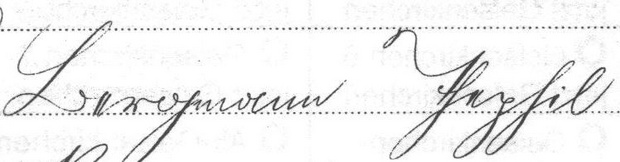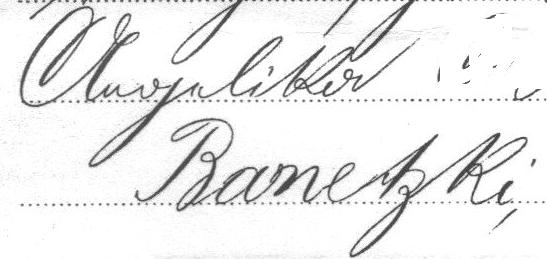
Was heißt das?
Ich hoffe, dass mir hier jemand helfen kann. Das Foto 1 zeigt einen Ausschnitt aus einer Geburtsurkunde von 1930. Es müsste sich um eine Berufsbezeichnung handeln. Leider habe ich keine Ahnung, was das bedeuten soll.
Das zweite Foto ist ebenfalls eine Geburtsurkunde, diesmal von 1903. Hier handelt es sich wahrscheinlich um eine Berufsbezeichnung, gefolgt von einem männlichen Vornamen.
Foto 3 müsste ein weiblicher Vorname sein, gefolgt von einem Nachnamen.
Ich habe das Gefühl, der Standesbeamte hat frei Schnauze irgendwas geschrieben, reines Sütterlin ist das nicht.
Beim dritten Bild lese ich »Angelika Ranetzki«, kann das sein?
Nach meiner Interpretation heißen müssten die Texte so lauten:
1. Bergmann Thephil
2. Hilfsweichenwärter
3. Angelika Banetzki
Was soll bitte Tephil bedeuten?
@Kathrinvdm: Ein R hat doch keine Schlaufe wenn man es verbunden schreibt, die kann doch eigentlich nur beim B entstehen, oder?
Edith hat was gefunden: Siehe z. B. Seite 146 nach Googles Zählung in Hertzsprungs Lehrbuch der Kalligraphie von 1854.
Ich habe das Gefühl, der Standesbeamte hat frei Schnauze irgendwas geschrieben, reines Sütterlin ist das nicht.
Kein Grund, unsere ehrenwerten Vorfahren zu diskriminieren, nur weil wir heute keine Kurrentschrift mehr gewohnt sind. :-)
Bild 1: Bergmann Thephil (ich habe eigentlich "Theophil" erwartet, erkenne aber beim besten Willen kein "o"; ansonsten eine sehr schöne Handschrift ...)
Bild 2: Hilfsweichenwärter (was es alles für Berufe gegeben hat ...)
Bild 3: "Angelika" stimmt sicher, wie Kathrin ja schon entziffert hat; beim Nachnamen bin ich nicht sicher, ob es nicht eher ein "B" am Anfang ist ...
@Kathrinvdm: Ein R hat doch keine Schlaufe wenn man es verbunden schreibt, die kann doch eigentlich nur beim B entstehen, oder?
Bild 3: "Angelika" stimmt sicher, wie Kathrin ja schon entziffert hat; beim Nachnamen bin ich nicht sicher, ob es nicht eher ein "B" am Anfang ist ...
Nach meiner Interpretation heißen müssten die Texte so lauten:
1. Bergmann Thephil
2. Hilfsweichenwärter
3. Angelika Banetzki
Was soll bitte Tephil bedeuten?
An dem Wort bin ich auch hängen geblieben. Ich habe aber an Stelle des p ein y gelesen. Theyhil ist aber noch weniger sinnvoll als Thephil. Denn dass kann ein Schreibfehler vom Namen Theophil sein.
@Kathrinvdm: Ein R hat doch keine Schlaufe wenn man es verbunden schreibt, die kann doch eigentlich nur beim B entstehen, oder?
Aber das Kurrent-B sieht total anders aus. Das dritte Beispiel sieht so aus, als ob der Schreiber sich in Angesicht eines fremdländischen Namens mit der lateinischen Schrift auseinandergesetzt und gegen diese gewonnen hätte.
Ich denke auch dass das ein R und kein B ist. Das B ist zu weit weg von dem Gesuchten.
B:
R:
... da aber im Nachnamen (und nur dort) a und e lateinisch sind, würde ich lieber B lesen. Was auch besser zum Namen Ba®netzki/Barnitzke/Barnicke passen würde, ein häufig und variantenreich eingedeutschter slawischer Familienname ...
Der Familienname scheint aber eh nicht aus der gleichen Hand wie das "Angelika" zu stammen (man vergleiche mal die beiden k)
Ich lese auch "Banetzki", denn dieser Nachname ist ja in lateinischer, und nicht in deutscher Schreibschrift geschrieben.
... da aber im Nachnamen (und nur dort) a und e lateinisch sind, würde ich lieber B lesen. …
Namen wurden früher oft in lateinischer Schrift geschrieben, um sie vom gewöhnlichen Text abzuheben. Das p in Thephil ist wirklich ein p (und nicht etwa ein y), das wird in Kurrent so geschrieben.
Ein unten offenes B in der lateinischen Schreibschrift sieht man bspw. auf dieser Abbildung:
Der Familienname scheint aber eh nicht aus der gleichen Hand wie das "Angelika" zu stammen (man vergleiche mal die beiden k)
Ich vermute ohnehin, daß Angelika und Banetzki nicht zusammengehören. Aufgrund des Kommas nach Banetzki liegt nahe, daß jeweils der Vorname dem Namen nachgeordnet ist, daß Angelika also zu dem darüberstehenden Namen gehört, der hier nicht zu sehen ist, während der Banetzki zuzuordnende Vorname unten abgeschnitten ist. Das würde erklären, daß Angelika und Banetzki unterschiedliche Schreiber haben, einen Kurrent- und einen Lateinschreiber.
Der Familienname scheint aber eh nicht aus der gleichen Hand wie das "Angelika" zu stammen (man vergleiche mal die beiden k)
Nanu? Mir scheinen die beiden k eher ein starker Hinweis darauf zu sein, dass es sich sehr wohl um die gleiche Hand handelt. Auch Neigung und Strichstärke sind identisch, und sogar die Proportionen ähneln sich, wenn man einmal davon absieht, dass die lateinische Schreibschrift eine grössere n-Höhe hat.
Ja, natürlich, ich meinte das Antiquabeispiel, das Axel Jagau ausgegraben hat.
Ja, der „Theopfiel“ war mir auch gleich aufgefallen. Scheint ja ein schwieriger Name zu sein… ;-)